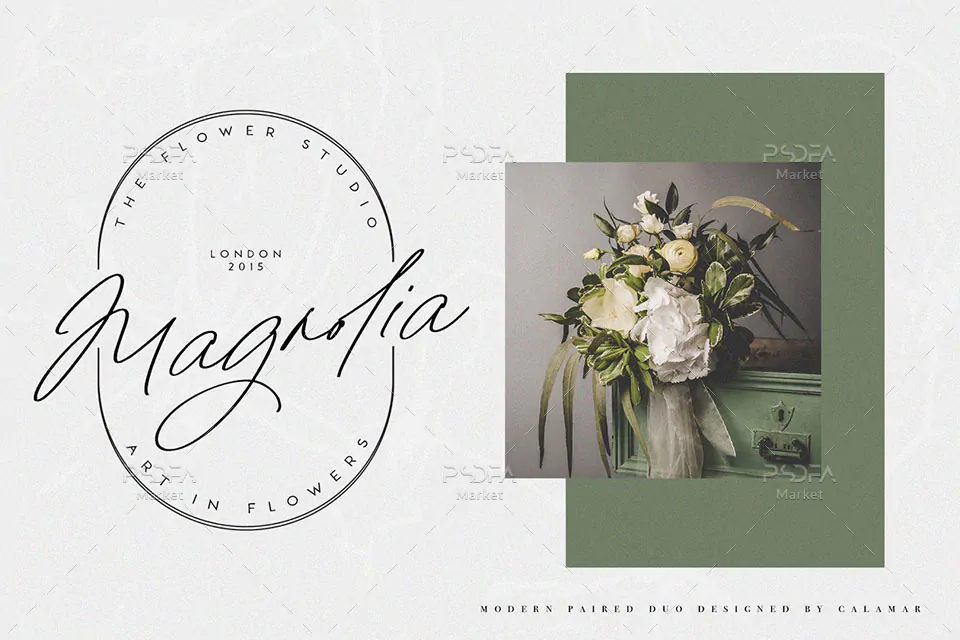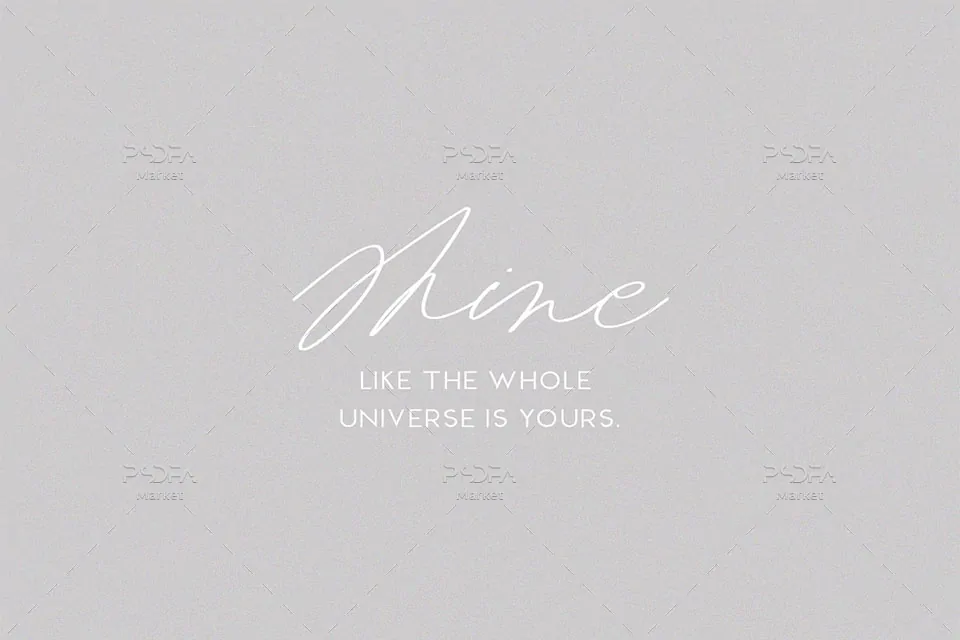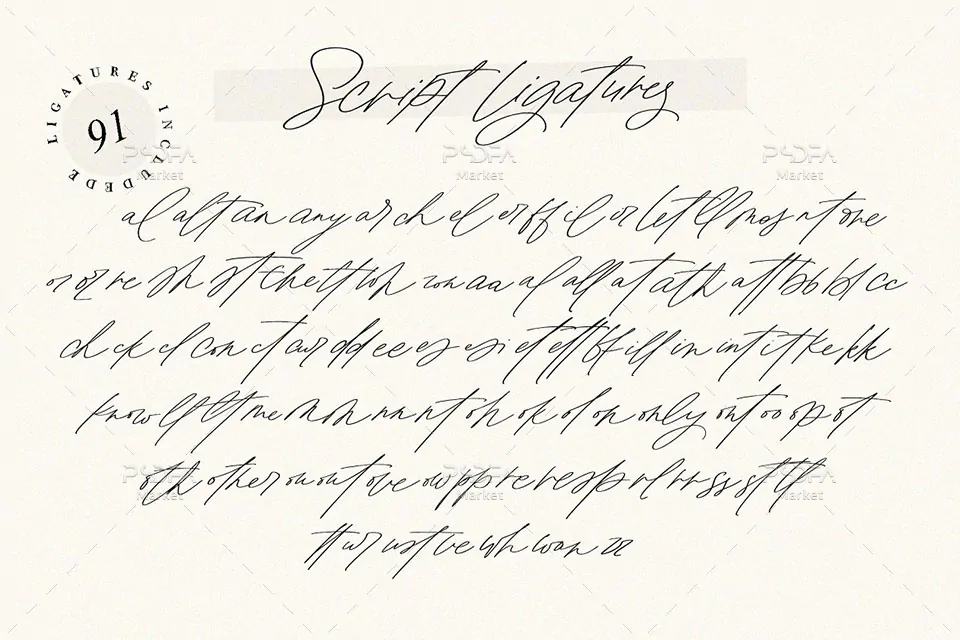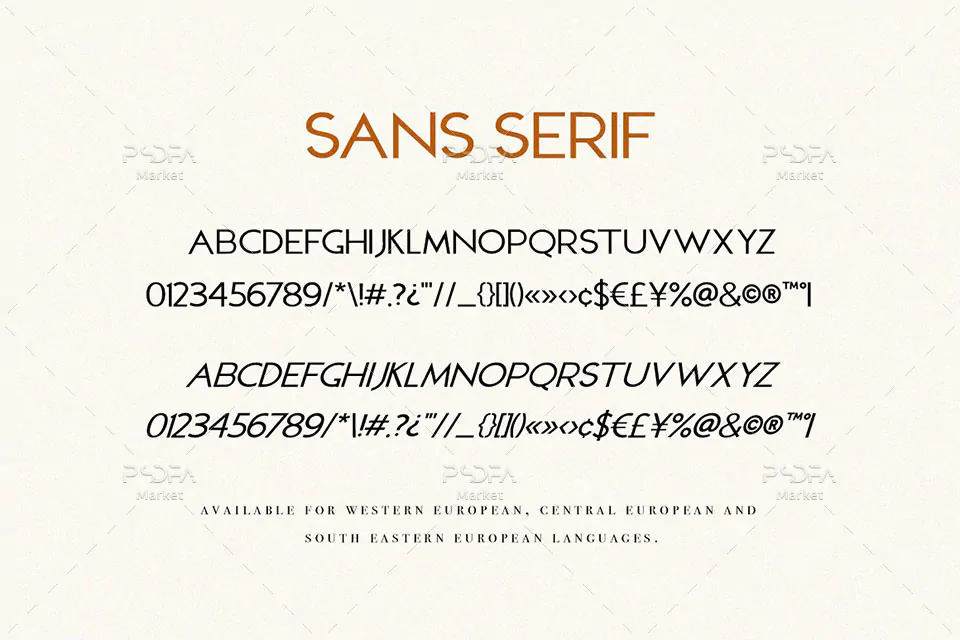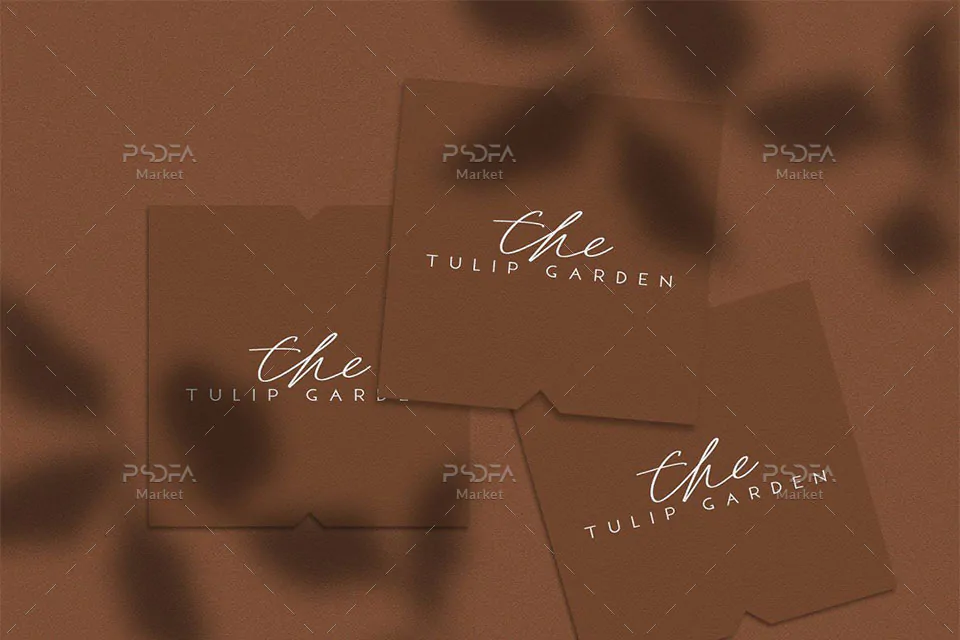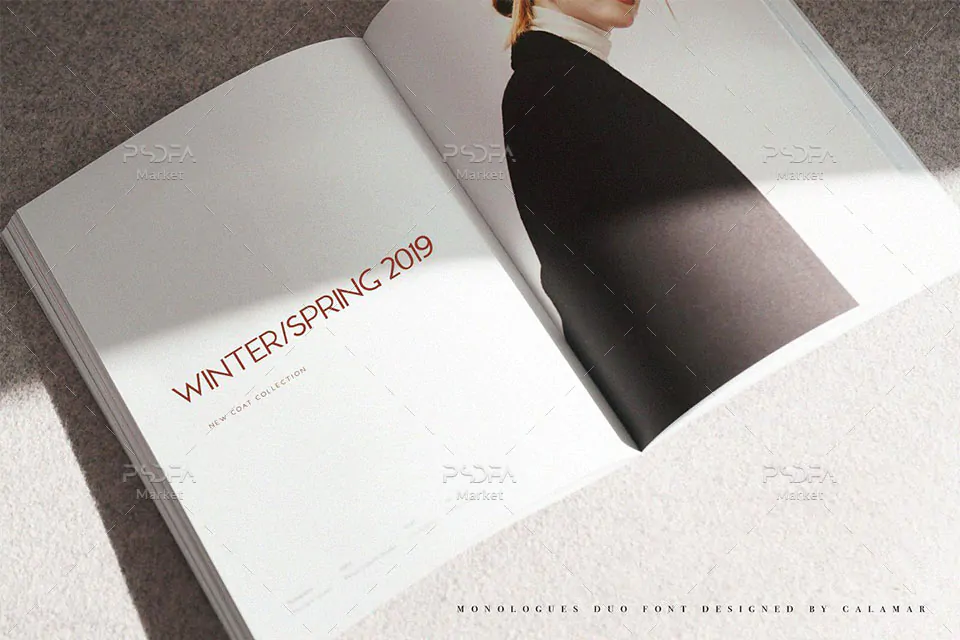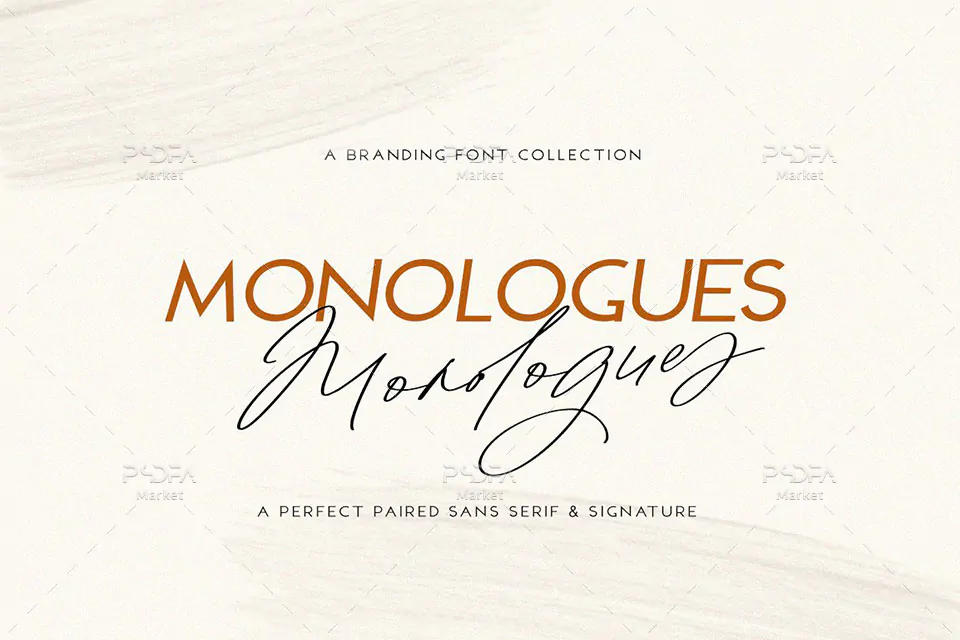
فونت انگلیسی طراحی لوگو Monologues به همراه نسخه سنس سریف مجموعهای از 2 قلم فوق العاده زیبا است که مناسب جهت استفاده در طرحهای گرافیکی مختلف به خصوص طراحی انواع لوگو و … میباشند. این 2 فونت زیبا در قالب 3 فایل OTF در فایل محصول قرار دارد که با نصب آنها در پوشه فونتهای سیستم میتوانید از این فونت انگلیسی در تمام نرم افزارهای گرافیکی و تایپ متون همچون فتوشاپ، افتر افکت، پریمیر، ورد، پاورپوینت و … استفاده کنید.
فونت Monologues در وزن معمولی (Regular) طراحی شده است که میتوانید از آن در طراحی انواع کارت تبریک، کارت پستال، کارت ویزیت، کارت عروسی، کارت دعوت، طراحی لوگو، کاور آلبوم موزیک، طراحی انواع بنر، پوستر، تراکت، تقویم و دیگر طرحهای گرافیکی استفاده کنید.
- نام فونت: Monologues